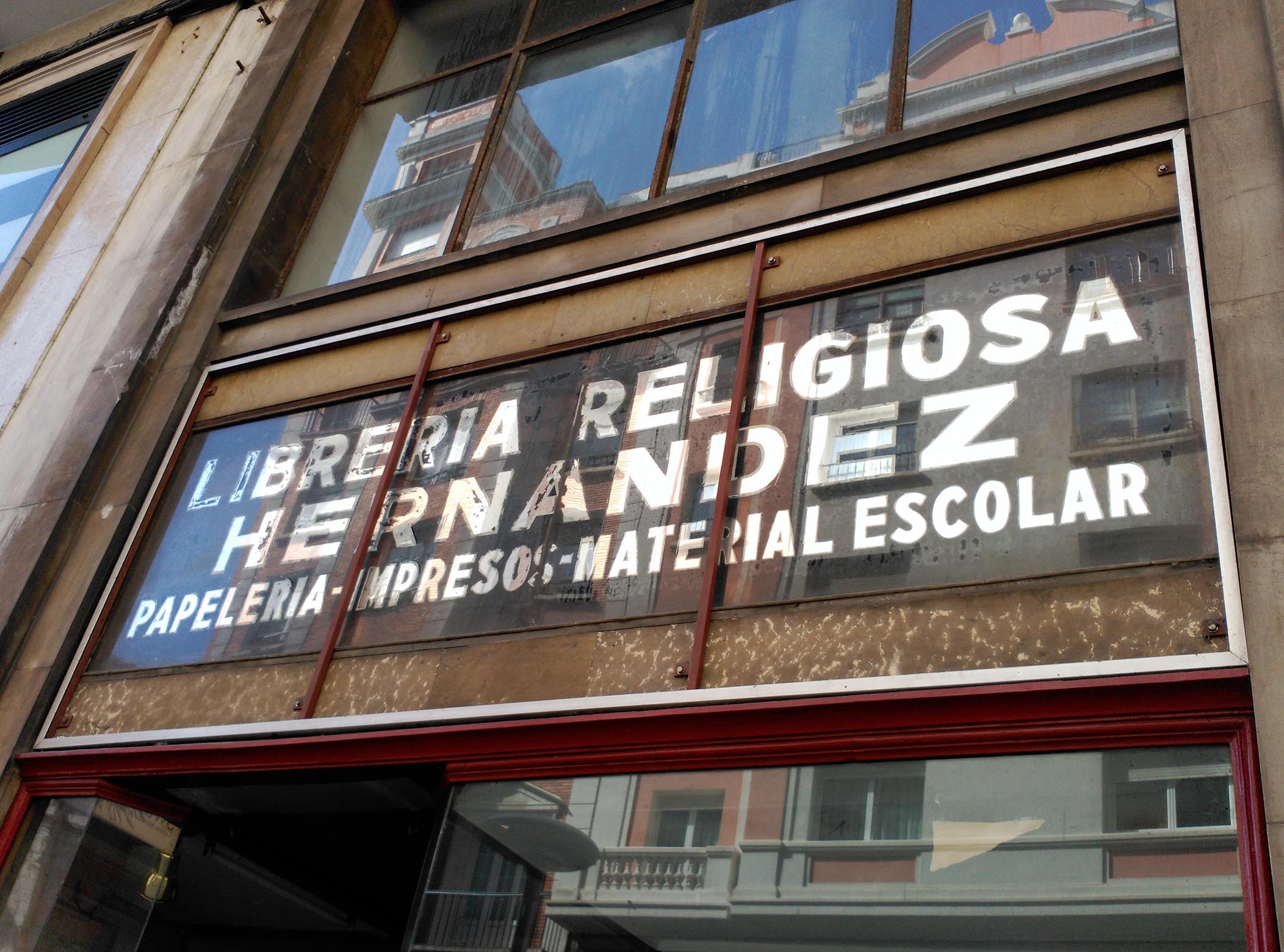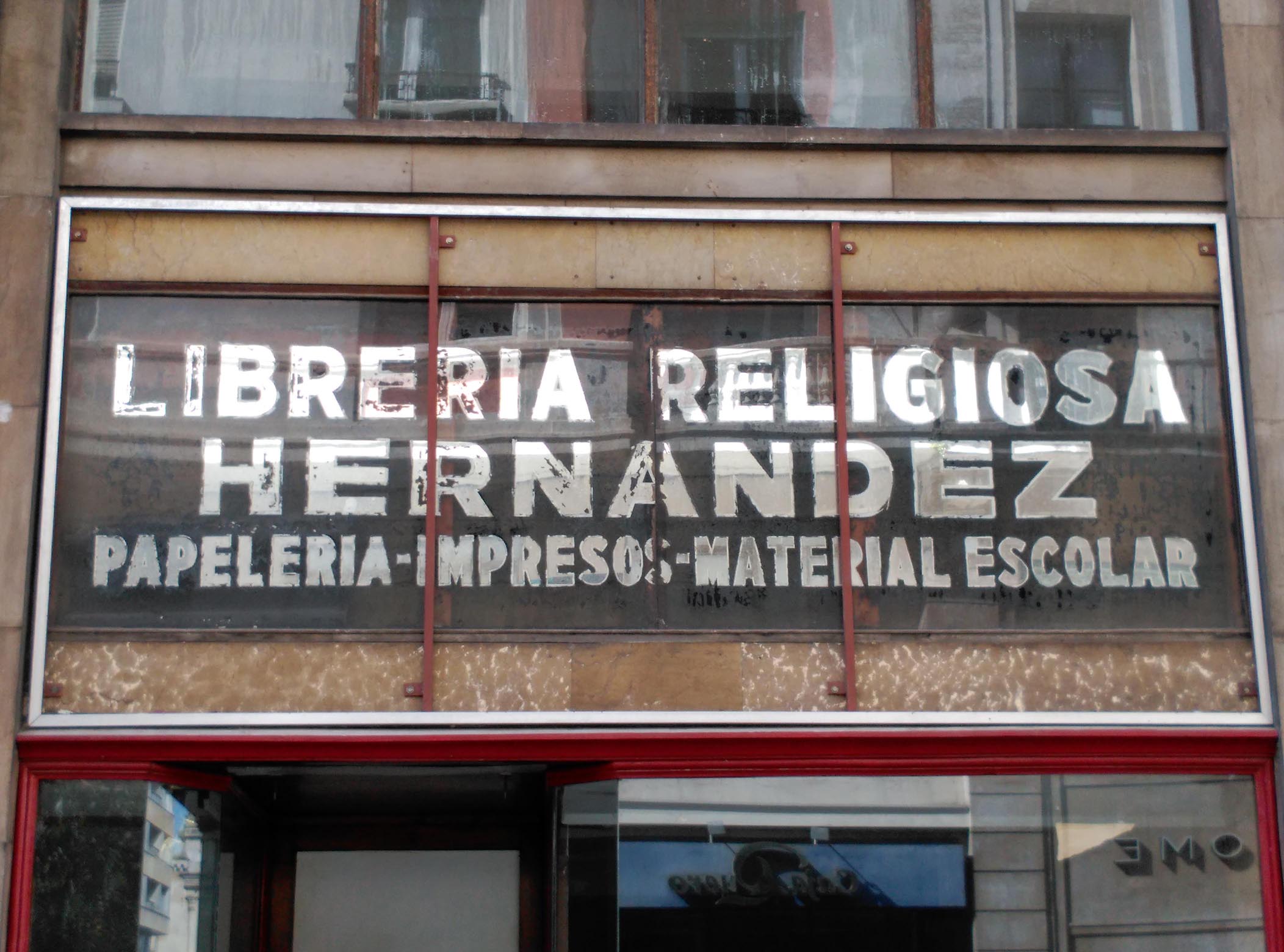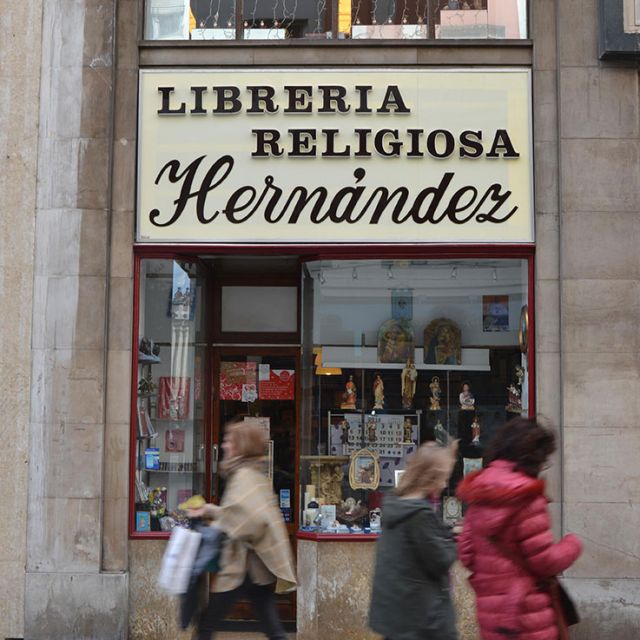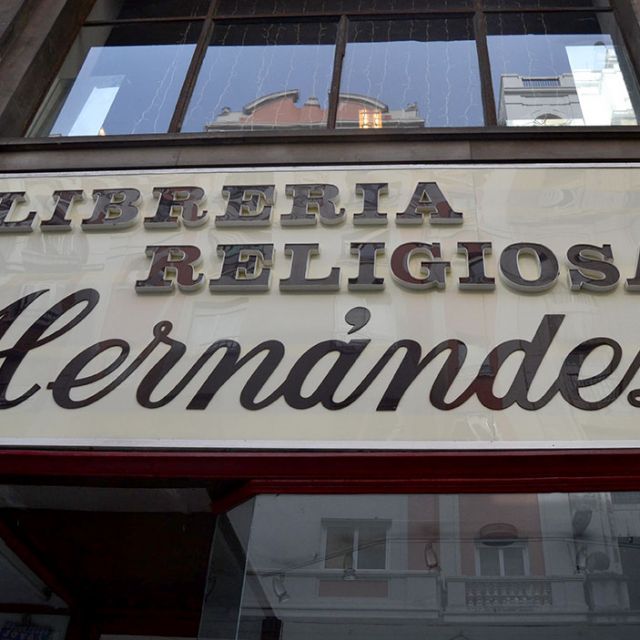
Libreria Religiosa Hernández
Aunque actualmente la tienda sigue abierta en la calle Cádiz, tras su cierre y conversión en un nuevo negocio, la tienda conocida por todos, que estaba en Juan de Herrera nos desveló una pequeña sorpresa.
Al desmontar el rótulo que hasta ahora todos conocíamos hecho en pvc con una mezcla de tipos y en relieve, el cual tenía cerca de 20 años, emergió el original en vidrio, rotulado. El original.
Cierto es que esta tienda con más de un centenar de años en activo (fue fundada en 1903 por Benito Hernández) ha pasado por distintas ubicaciones: La primigenia estaba en la antigua calle Ribera; tras el Incendio de 1941 se ubicaron en Juan de Herrera, donde llevaban cerca de 70 años ubicada hasta su cierre en este año. Ahora está en la calle Cádiz.
Nos hemos puesto en contacto con ellos para saber un poco más y esperamos despejar todas estas dudas, así como saber dónde ha ido a para el rótulo de esta tienda mítica de la ciudad. Seguiremos informando 😉
Actualizado 2019: En febrero de este año se ha anunciado el cierre definitivo de esta tienda centenaria tras más de 120 años de actividad.
El rótulo en cristal que apareció durante las obras de remodelación (Fotos Abril 2014)